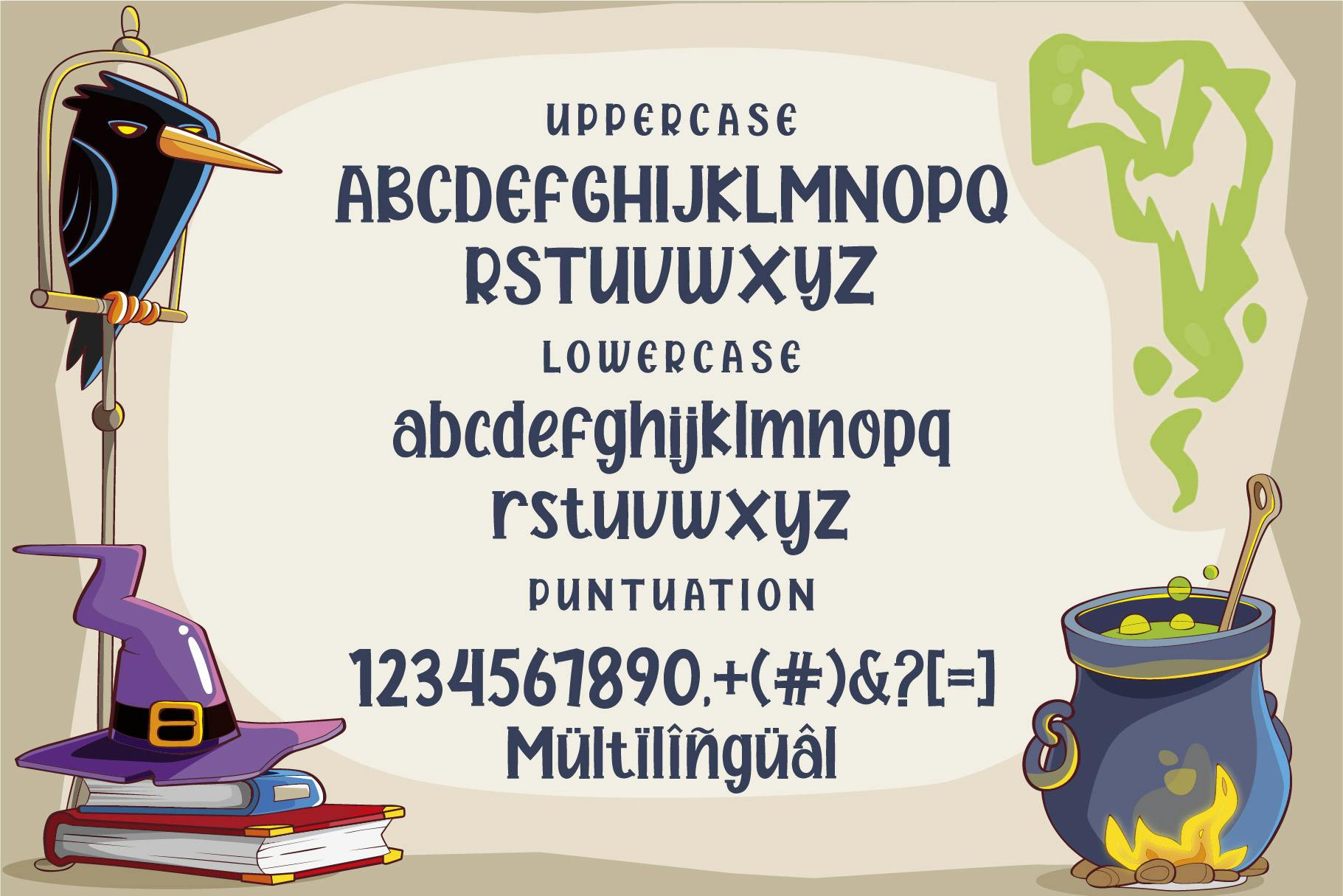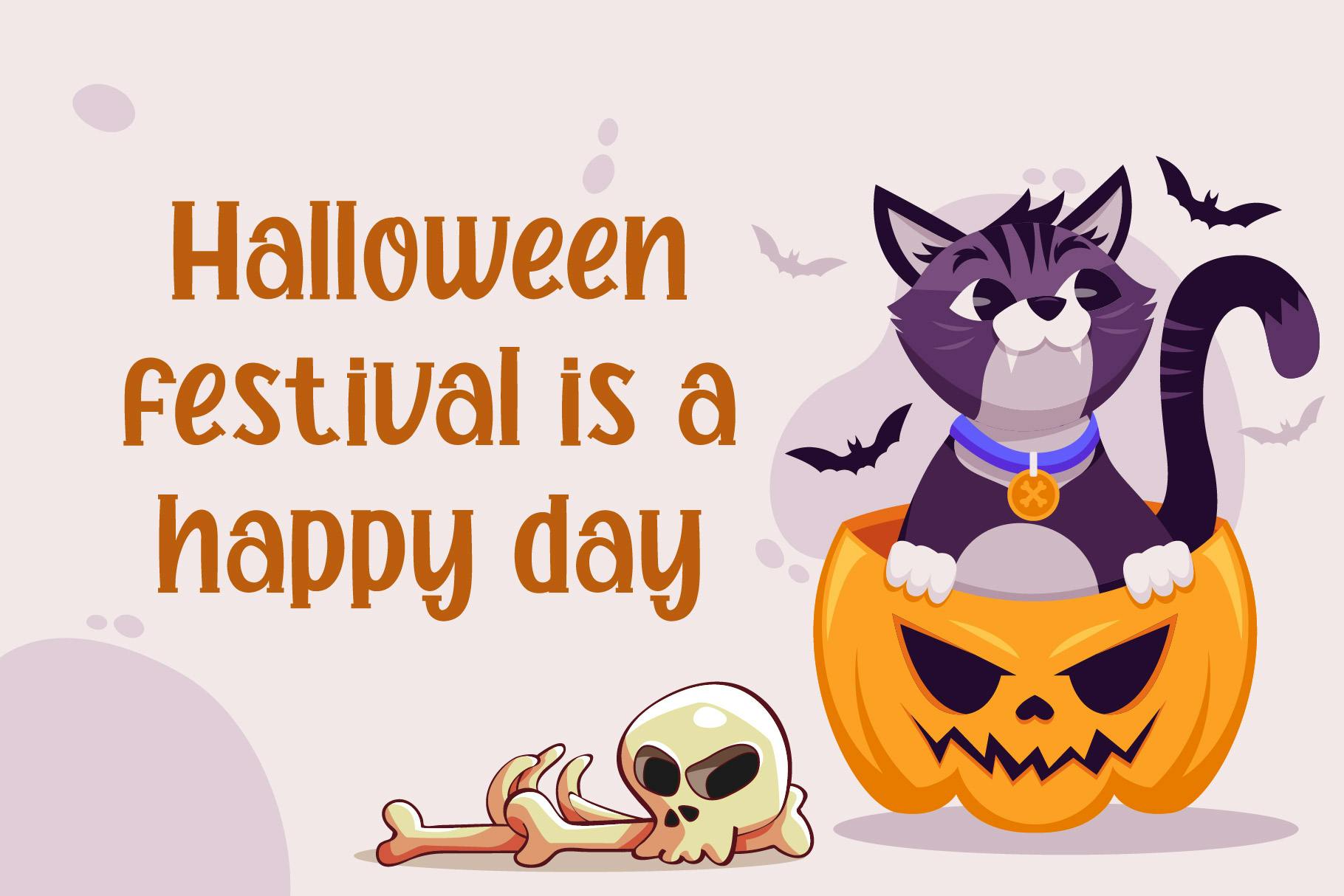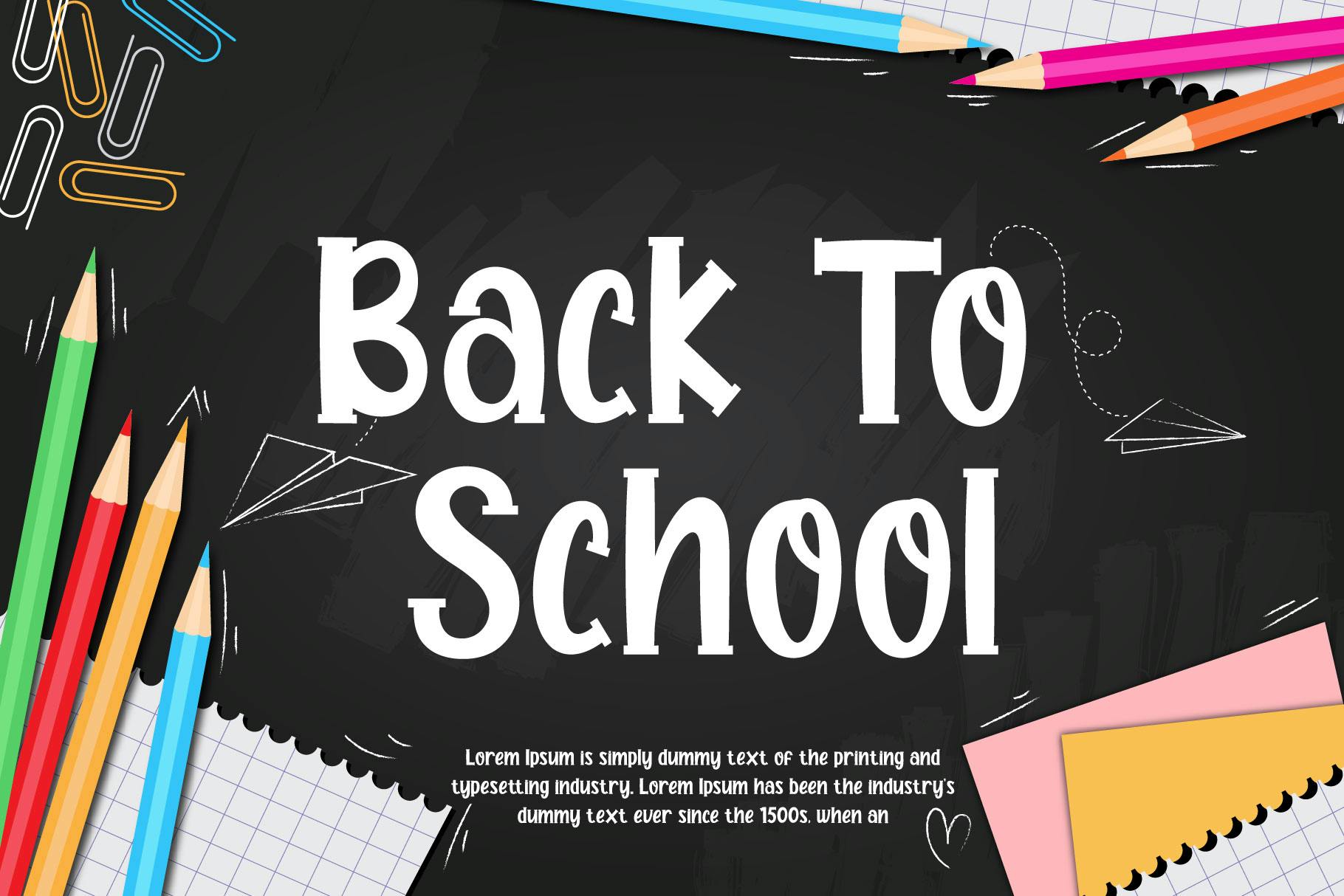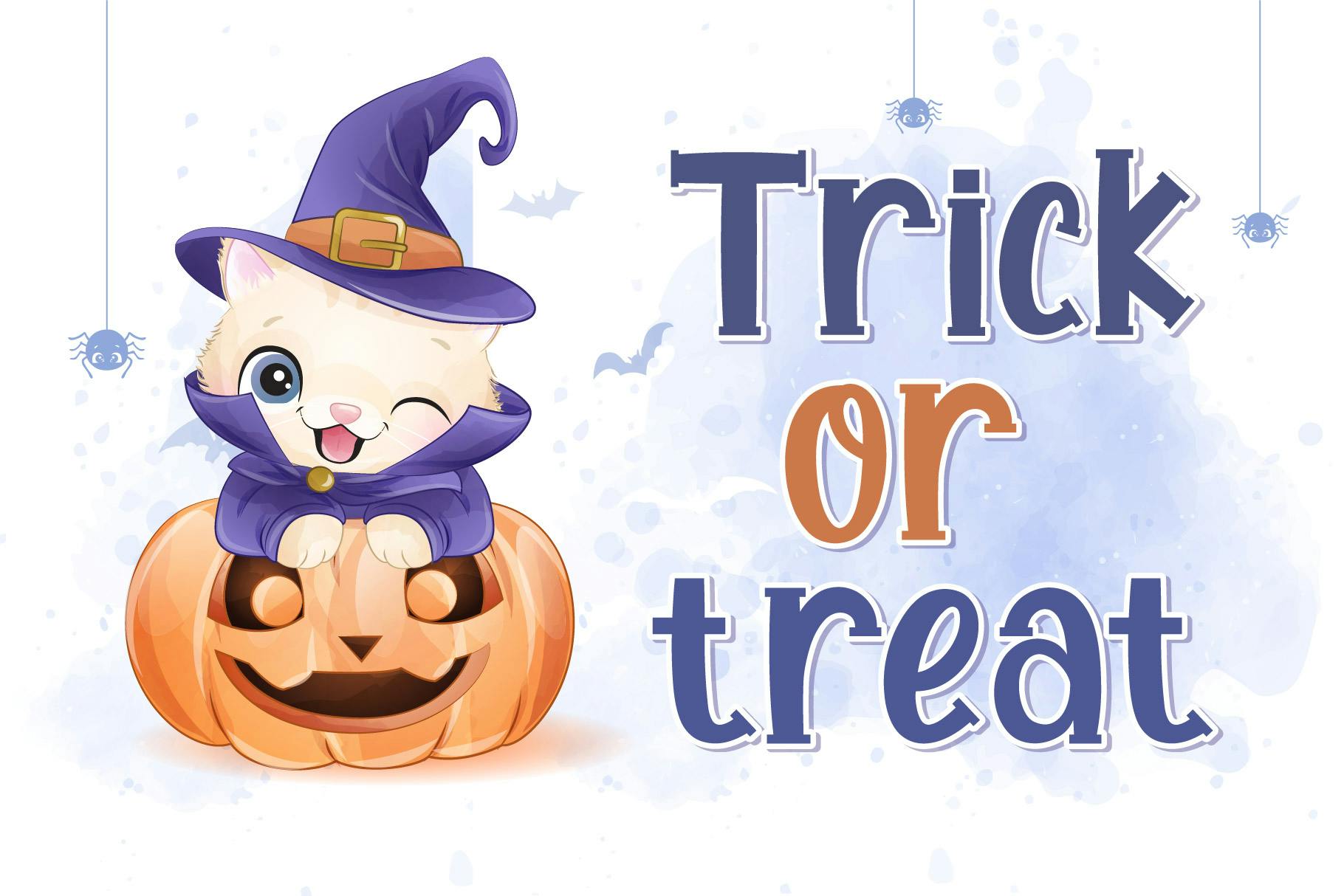
فونت هالووین دی یک فونت نمایش جذاب و مدرن است که برای طراحیهای گوناگون مناسب میباشد. این فونت میتواند در محصولاتی مانند دستسازهها، بستهبندی محصولات، نقلقولها، طراحی محصولات، آثار هنری، برچسبها، عکاسی، واترمارکها، لوگوها و برندینگ استفاده شود.